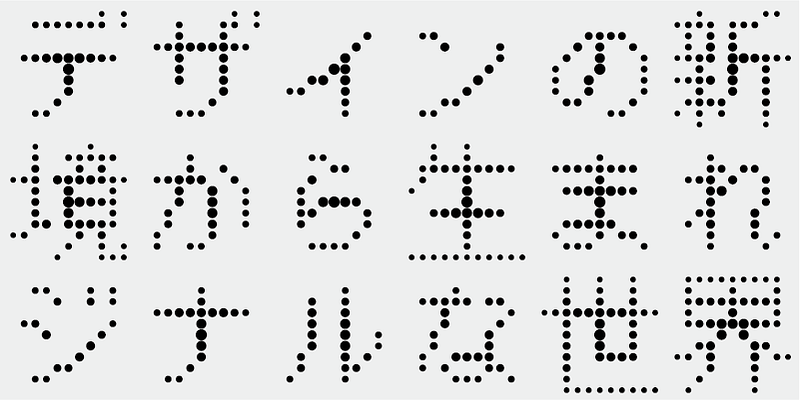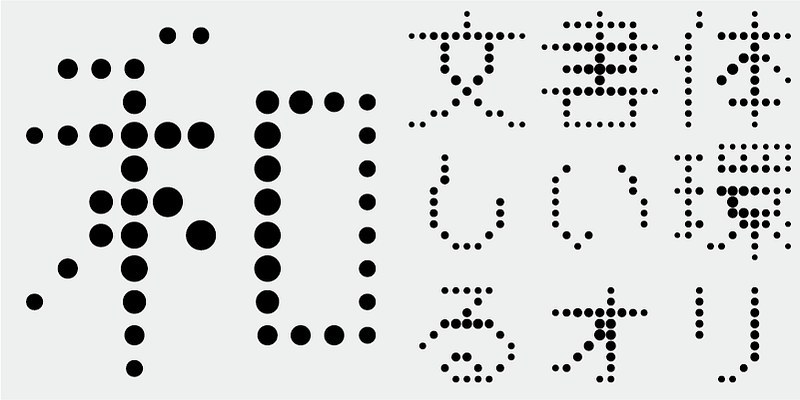
단순화를 위해 사용된 11x11 그리드 내에서 우수한 가독성을 유지합니다. 문자의 중심에서 멀어질수록 점이 작아져 금방 사라질듯한 눈송이처럼 보입니다.
이 서체는 Japan Typography Annual Awards 2006에서 최우수 작품으로 선정되었습니다.
이 글꼴에는 신문사, 출판사, 언어 연구소가 만든 문자 빈도표에서 선정된 가장 많이 사용되는 일본어 한자 1,000개와 더불어 206개의 가나 문자와 구두점이 포함되어 있습니다.
오늘날 일본어 글꼴 제작에서는 JIS 표준의 7,000자가 필수로 간주됩니다. 그러나 모든 글꼴에 정말 7,000자가 필요할까요? 사진 식자 시대에는 훨씬 적은 수의 문자가 필요했습니다. 독립 서체 디자이너 그룹인 FONT1000은 그 간단한 질문으로 시작했습니다. 일본어 서체에 필요한 최소 1,000자의 한자(표의 문자)를 선택했고 이를 지원하는 서체와 글꼴을 적극적으로 만들었습니다. 이 1,000자의 한자 문자 세트는 신문사, 출판사, 언어 연구 기관 등에서 수집한 문자 빈도 데이터를 사용하여 선택되었으며 가나 음절 문자 및 구두점도 포함합니다. FONT1000은 2001년에 25명의 디자이너와 25개의 서체로 시작했습니다. 현재는 130개의 서체를 보유 중이고 거의 40명의 멤버를 포함하도록 성장했으며, 더 많은 문자가 있는 글꼴 작업이 가능하게 되었습니다.